La producción de la primera cinta de Avatar (cuya reseña de 2009 escrita por Leo Prieto para FayerWayer pueden leer aquí) costó bastante dinero, más de USD $237 millones y al final se terminó convirtiendo en la cinta más taquillera de la historia. James Cameron tiene un talento innegable para algunas cosas.
Por ello a medio mundo ha mantenido fascinados y desconcertados la decisión de utilizar la tipografía gratuita de Papyrus como la fuente para el título de la película.
Durante años todo el material promocional y de imagen del filme utilizó esta tipografía que no es Comic Sans pero sí podría ser considerada como una de las más odiadas del planeta.
Por fortuna ahora que está por estrenar la segunda parte James Cameron ha decidido corregir su error de una forma elegante: abriendo la billetera.
Avatar 2 abandona las tipografías gratuitas
Ahora hace pocos días se acaba de estrenar el primer avance oficial de Avatar 2: The Way of Water, o Avatar 2: el camino del agua, como se conocerá en América Latina.
Y fue ahí que, al final, apareció un detalle: el título de la película había cambiado su estilo de fuente sutilmente:
Esto resulta que no fue casualidad, ya que el diseñador John Roshell ha revelado en una entra de su blog que Lightstorm Entertainment, la compañía de James Cameron, le encargó crear una tipografía completamente nueva para darle nueva imagen a Avatar 2.
Fue así como Papyrus desapareció para ser relevada por una fuente un poco similar pero con identidad propia, aunque no lo parezca tanto a simple vista:
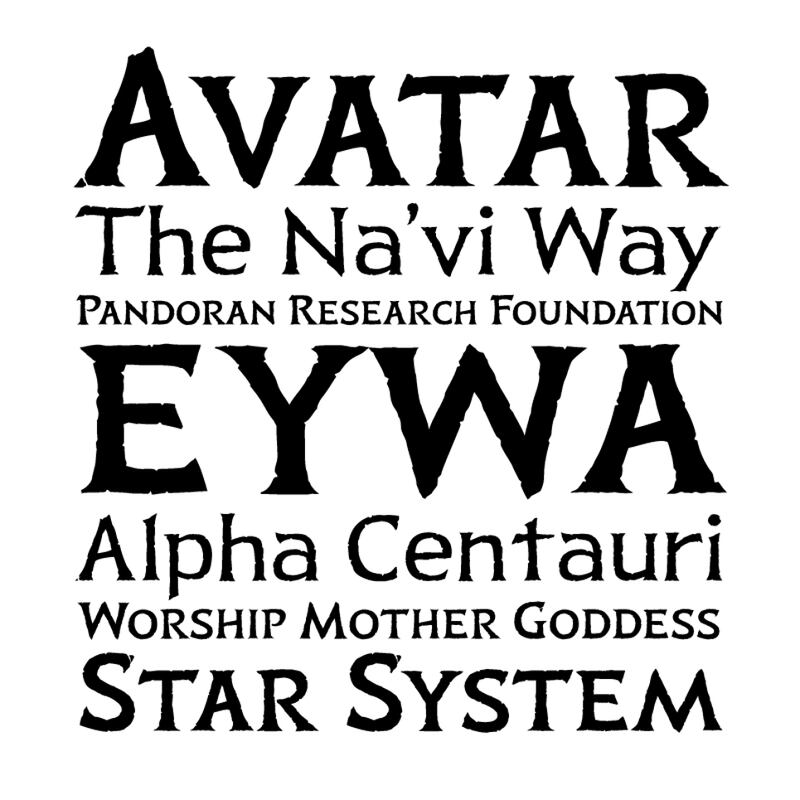
“A diferencia de muchos obsesionados de las tipografías, creo que Papyrus es en realidad una fuente muy atractiva. De hecho debo admitir que a mi parecer no encajaba mal con el logotipo original de Avatar.”
Son las palabras con las que el artista justifica las decisiones previas de James Cameron, aunque no pierde la oportunidad de señalar Papyrus igual que aparece igual en cajas de marca de té y hasta discos de Shakira.
Al ver esta nueva tipografía vemos bastantes similitudes con la desdeñada. Aunque sus contornos son más gruesos y estilizados.